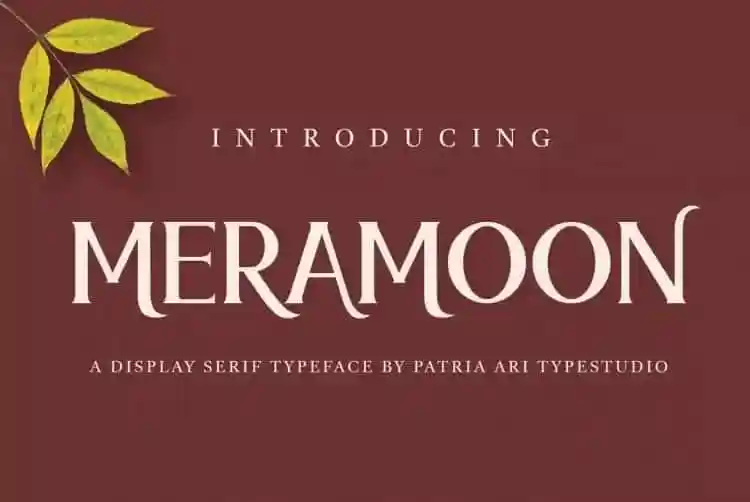
Meramoon Serif é uma fonte serif que traz consigo um tom elegante e sofisticado. Em formato condensado, ela destaca-se pela sua estrutura acentuada, com traços finos que lembram um arco-íris cortando o ar. O x-ponto de tamanho médio baixo faz deste fonte uma escolha perfeita para projetos como logomarcas e publicações em mídias sociais, onde cada detalhe é crucial. A Meramoon oferece um visual atraente que se adapta bem tanto às grandes aparições quanto aos textos mais detalhados. Combinada à exuberância da sua aparência única, Meramoon é uma escolha ideal para criação de identidades corporativas, publicidade, embalagens de produtos e design gráfico, tornando-a uma fonte imprescindível tanto para projetistas quanto para profissionais de marketing.